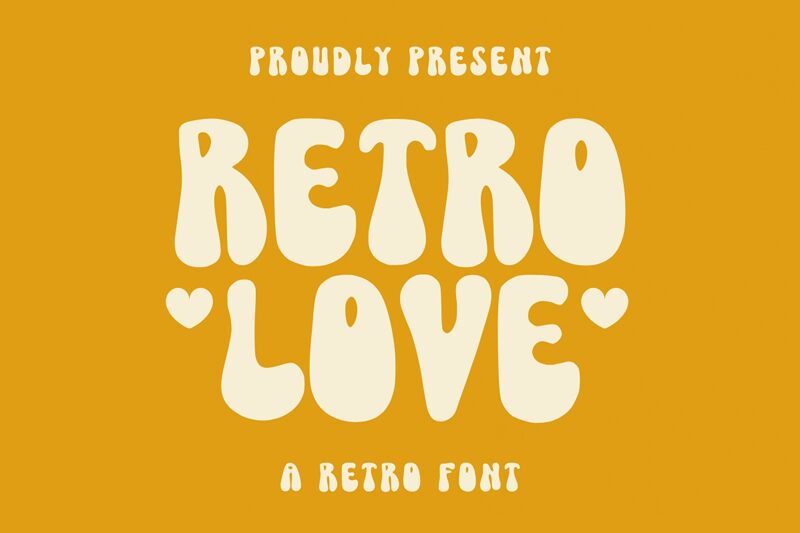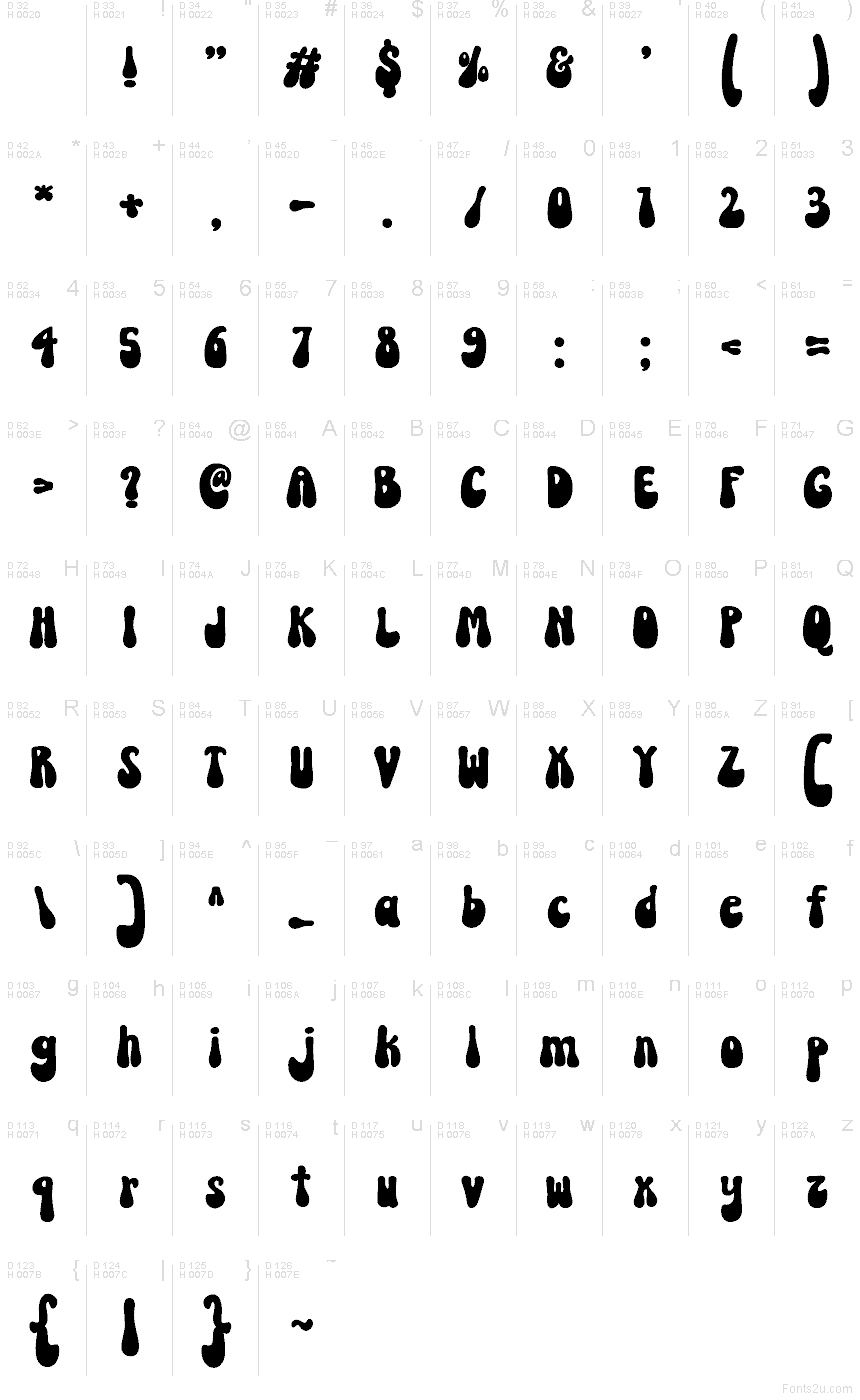
Retro Love od Masyafi Studio je bezplatné groovy displejové písmo s buclatými, měkkými tvary, které vycházejí z robustního stylu 70. let. Zaoblená konstrukce a lehce nepravidelný rytmus propůjčují písmu přátelský, plakátový vzhled, který má v sobě dostatek švihu na to, aby připomínal vintage popovou grafiku, nikoliv jen obyčejný font.
Díky široké siluetě skvěle funguje na obalech alb, brandingu kaváren, letácích, nálepkách i v nadpisech na sociálních sítích, kde je potřeba vnést trochu hřejivé nostalgie. Protože písmena působí plným, nafouklým dojmem bez zbytečných detailů nebo ostrých kontrastů, dodávají obalům i merchandise grafice veselý a výrazný hlas.